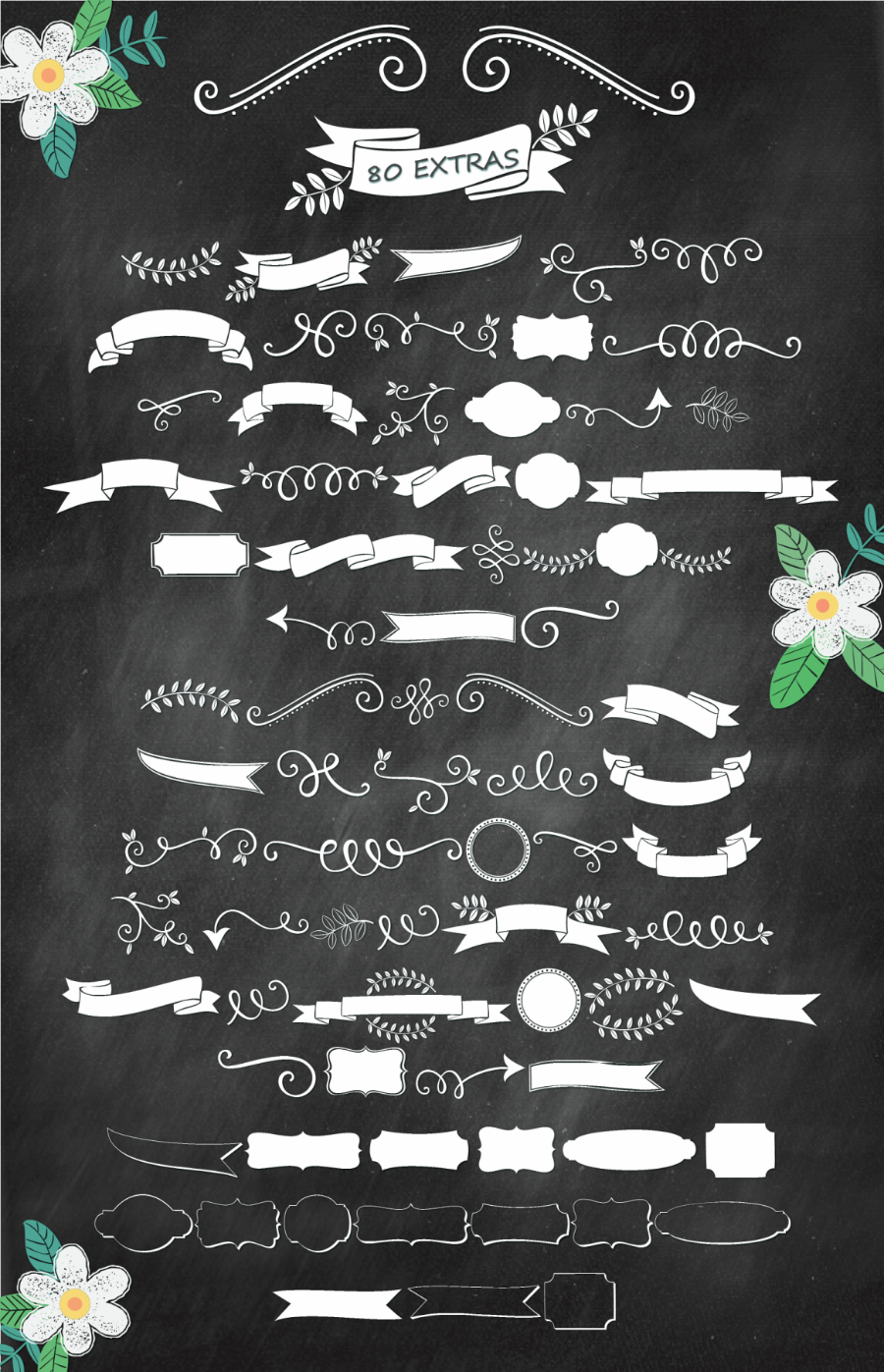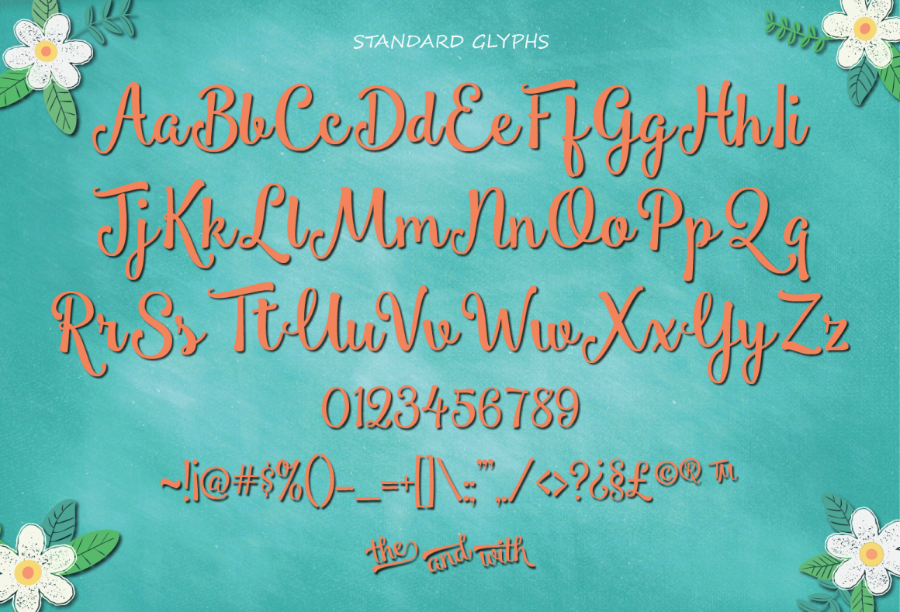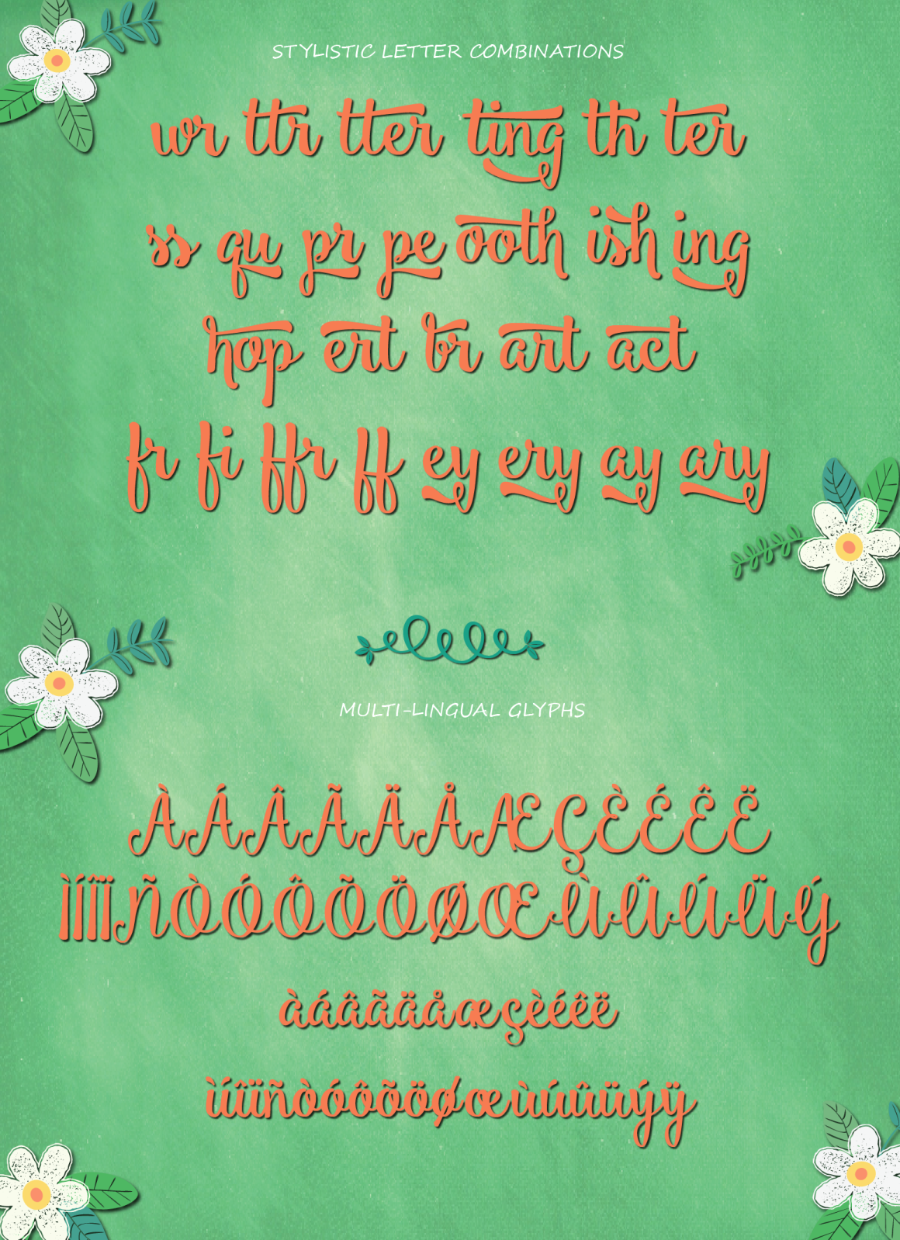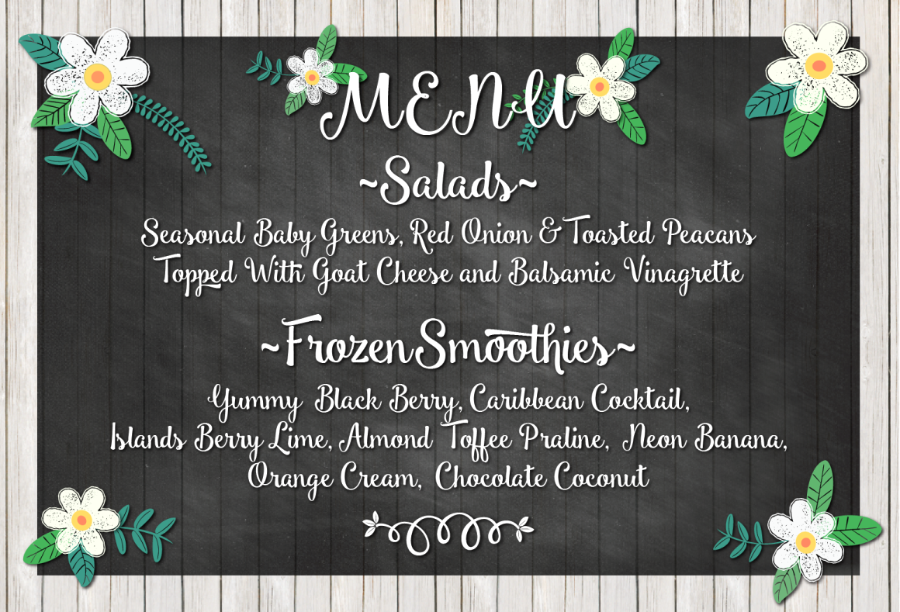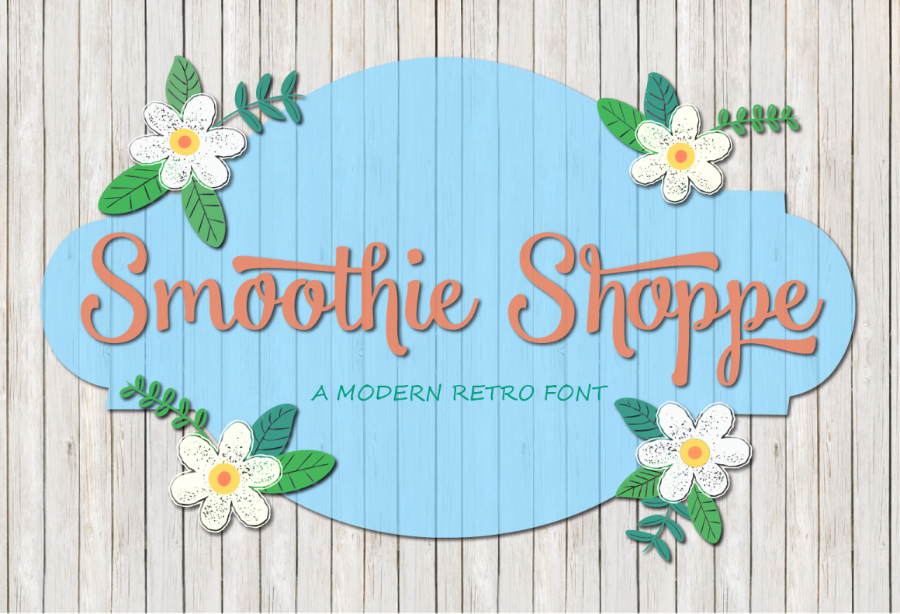
思慕雪专柜免费字体
冰沙专柜免费字体是一个大胆,但甜美,现代版的艾米莉Spadoni的最喜欢的复古显示字体。有趣,但干净的画笔风格脚本字母。它带有许多额外的字符组合。此外,用连字和花饰看上你的任何设计项目。此外,它提供了超过80个装饰品真棒奖金!框架,横幅,吨黑板风格的装饰品和涂鸦来装饰任何你的小心脏的愿望。